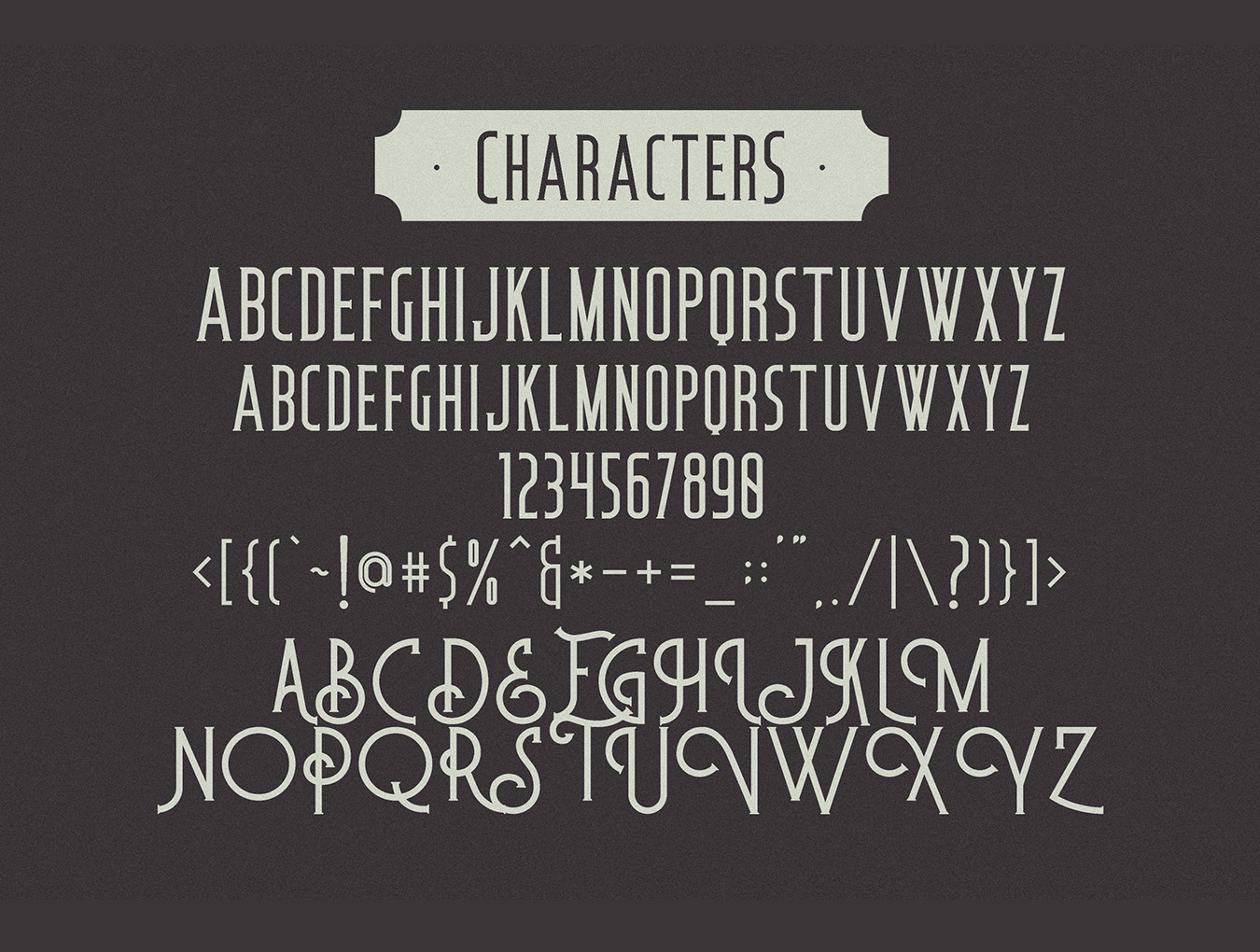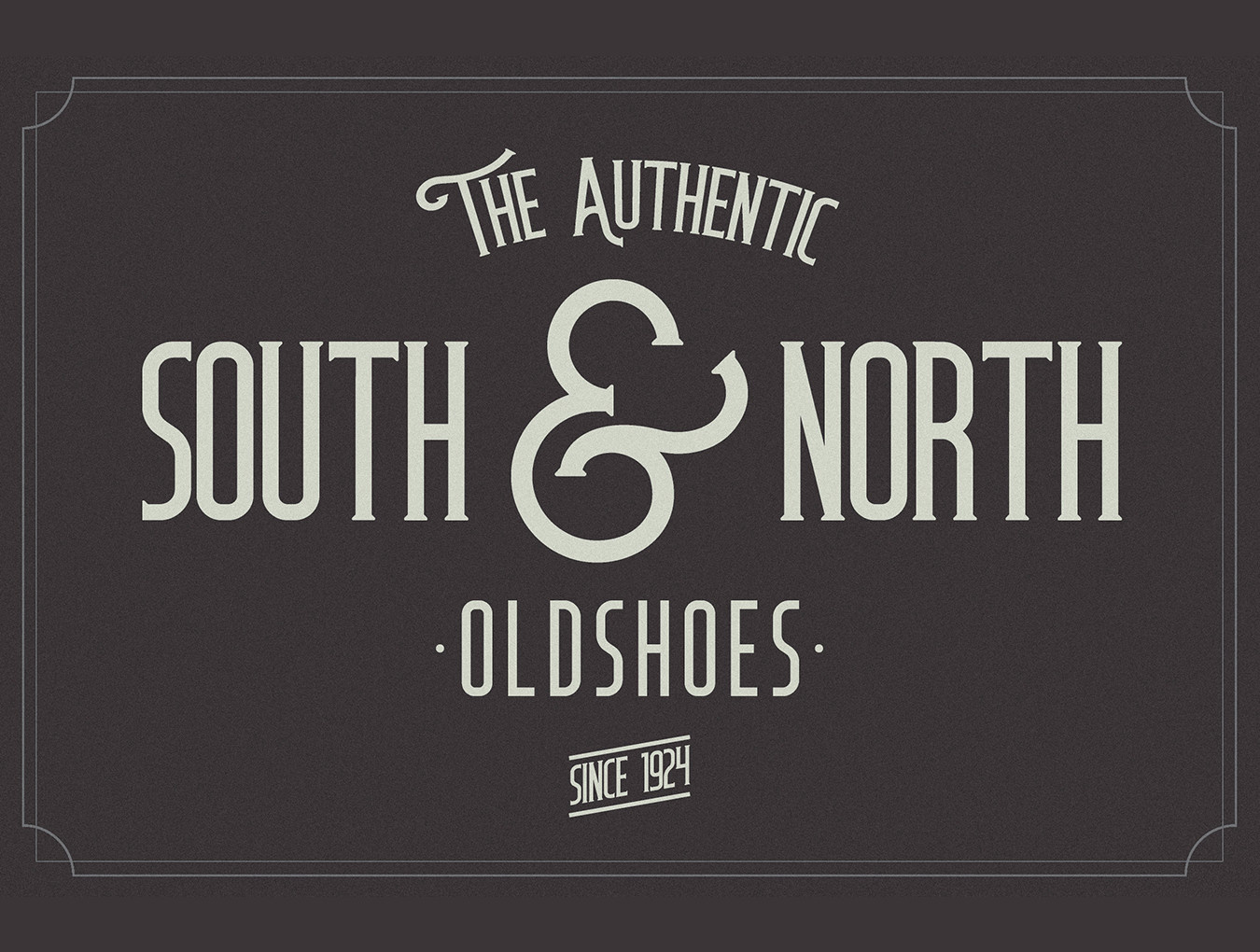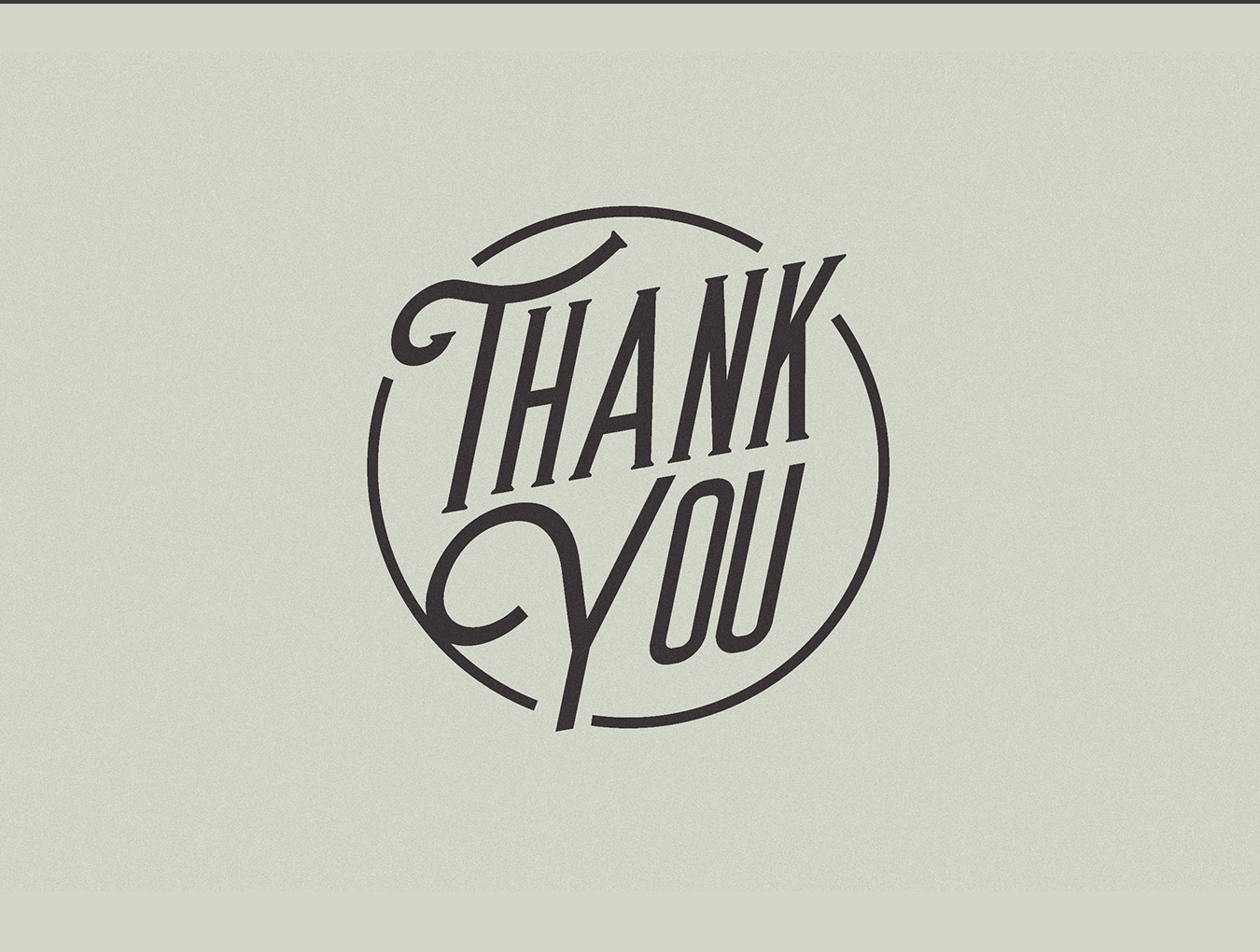
复古家庭衬线字体,四季
Vintage family serif typeface, The Seasons
The Seasons是一款受1800年底字体启发的字体。主题为复古,经典和复古。此字体适合设计复古海报,复古徽标,语标等的需求。 四季有四种风格:衬线,斜体衬线,圣衬线和圣斜体。 请享用!